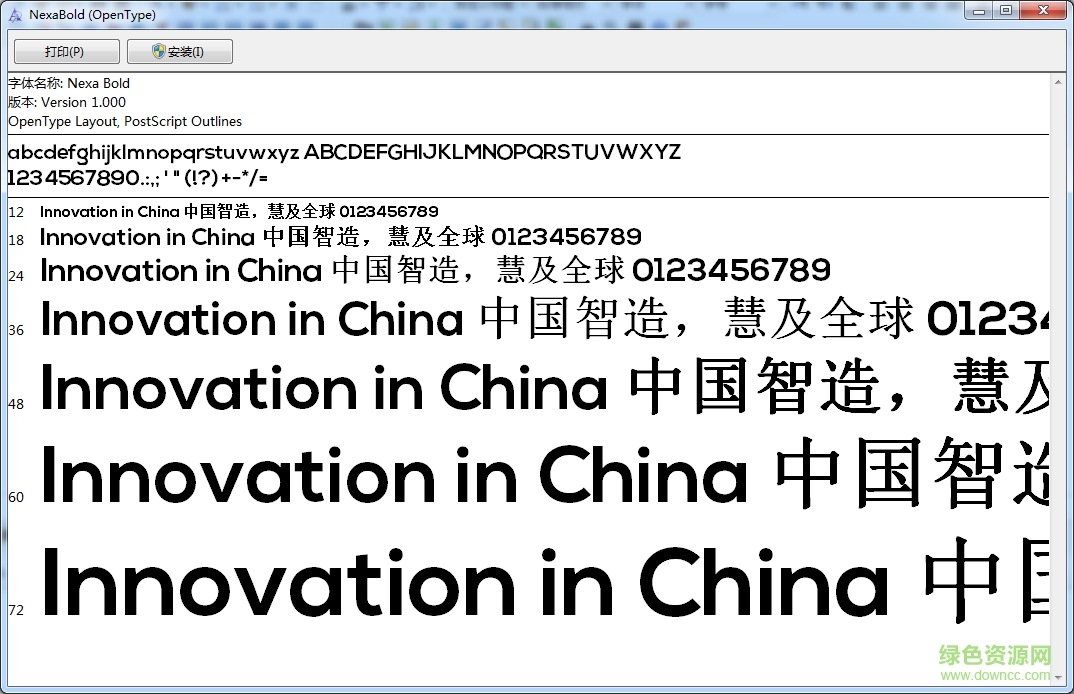
nexa heavy
nexa heavy字體是一款胖胖的的英文字體,筆畫特別粗壯,結(jié)構(gòu)嚴(yán)謹(jǐn),能給人傳達(dá)出強(qiáng)勁的意味,可廣泛應(yīng)用于廣告宣傳等商業(yè)領(lǐng)域,喜歡的小伙伴快來(lái)綠色資源網(wǎng)下載吧!
nexa heavy字體特點(diǎn)
字體風(fēng)格非常的大氣,字體粗黑,筆畫非常的粗重醒目,非常適合用于廣告字體和包裝印刷行業(yè)!